한글날을 맞이해서 무료로 배포하는 서체를 소개합니다.
지마켓 산스체
Gmarket Sans
G마켓 브랜드 아이덴티티를 담은 서체 "Gmarket Sans"를 소개합니다.
"Gmarket Sans" 는 다양한 브랜드, 판매자, 사용자가 함께 성장하며 가치를 나눌 수 있도록 만든 글꼴입니다.
이스타항공 이스타서체
편안한 말씨 이스타체
글꼴은 사람과 사람의 거리를 좁혀줍니다.
이스타항공의 글꼴은 고객이 듣고 싶은 이스타항공의 이야기를 편안한 말씨로 담았습니다.
여기 어때 잘난체고딕
잘난체는 여기어때의 BI특징을 모티브로 하여 만들어졌습니다.
여기어때 BI의 가장 큰 특징인 기둥의 시작과 맺음을 그대로 서체에 녹여내였으며
네모꼴의 꽉 찬 모듈로 BI가 주는 안정적인 느낌이 적용된 서체입니다.
쓰면 쓸수록 매력 만점!
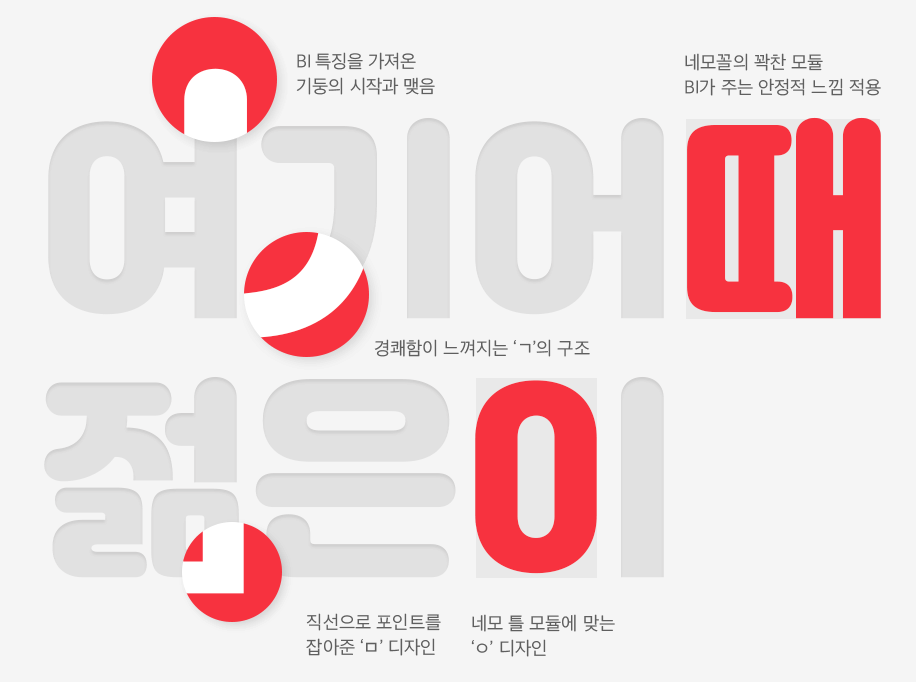
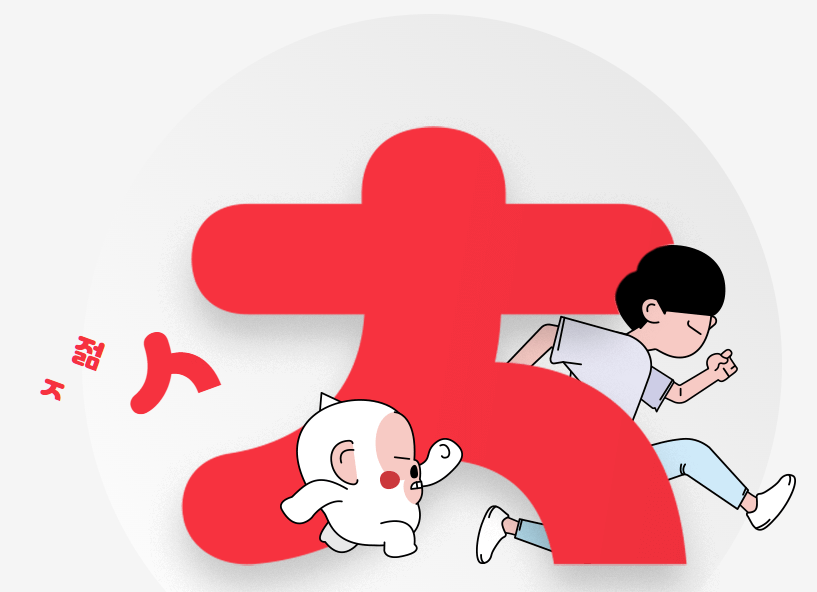
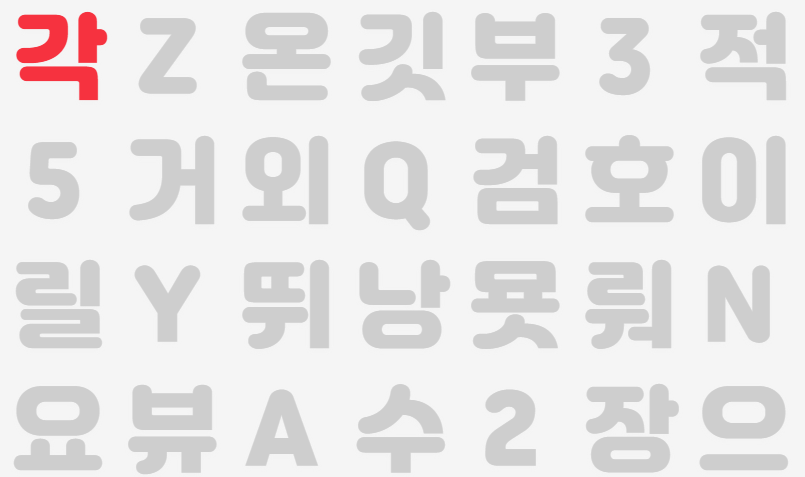
웅진식품 하늘보리체
웅진식품에서 577번째 한글날을 맞아 하늘보리체를 배포합니다.
청량한 하늘 속 뭉실뭉실 떠있는 구름이 떠오르는 하늘보리체를 다운로드 받으시고
일상 속 마음까지 쿨~해지고 싶을 때 하늘보리체를 사용해 보세요.